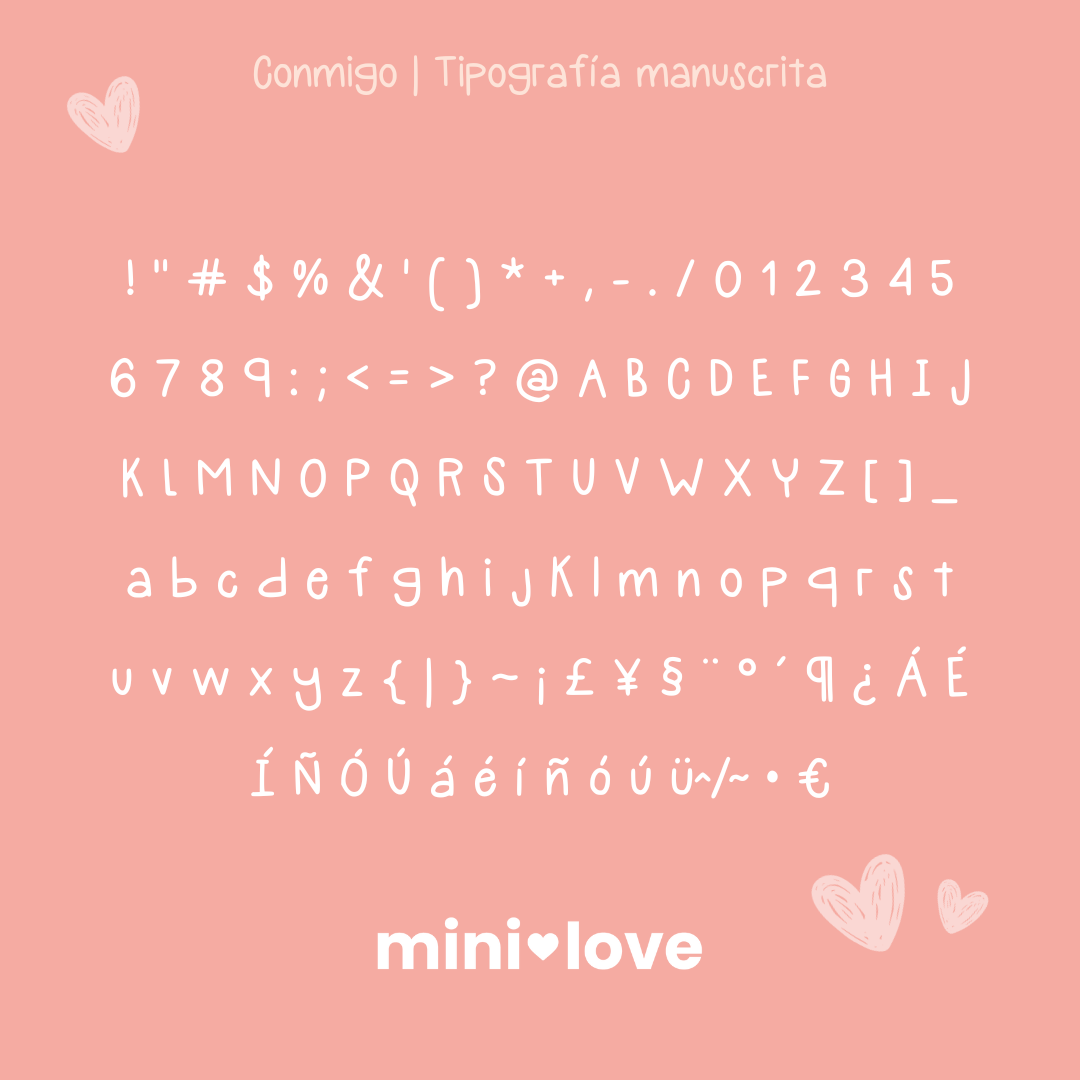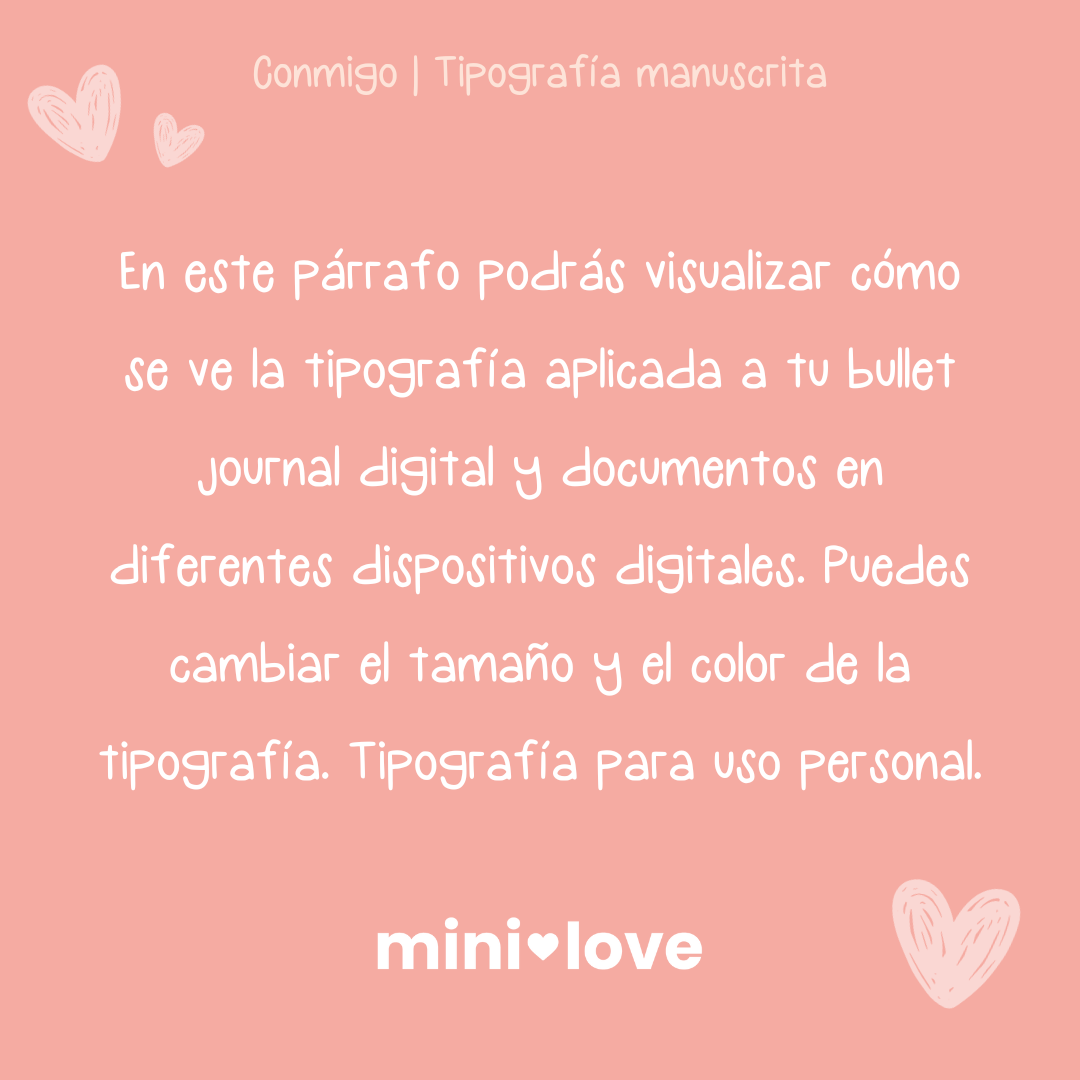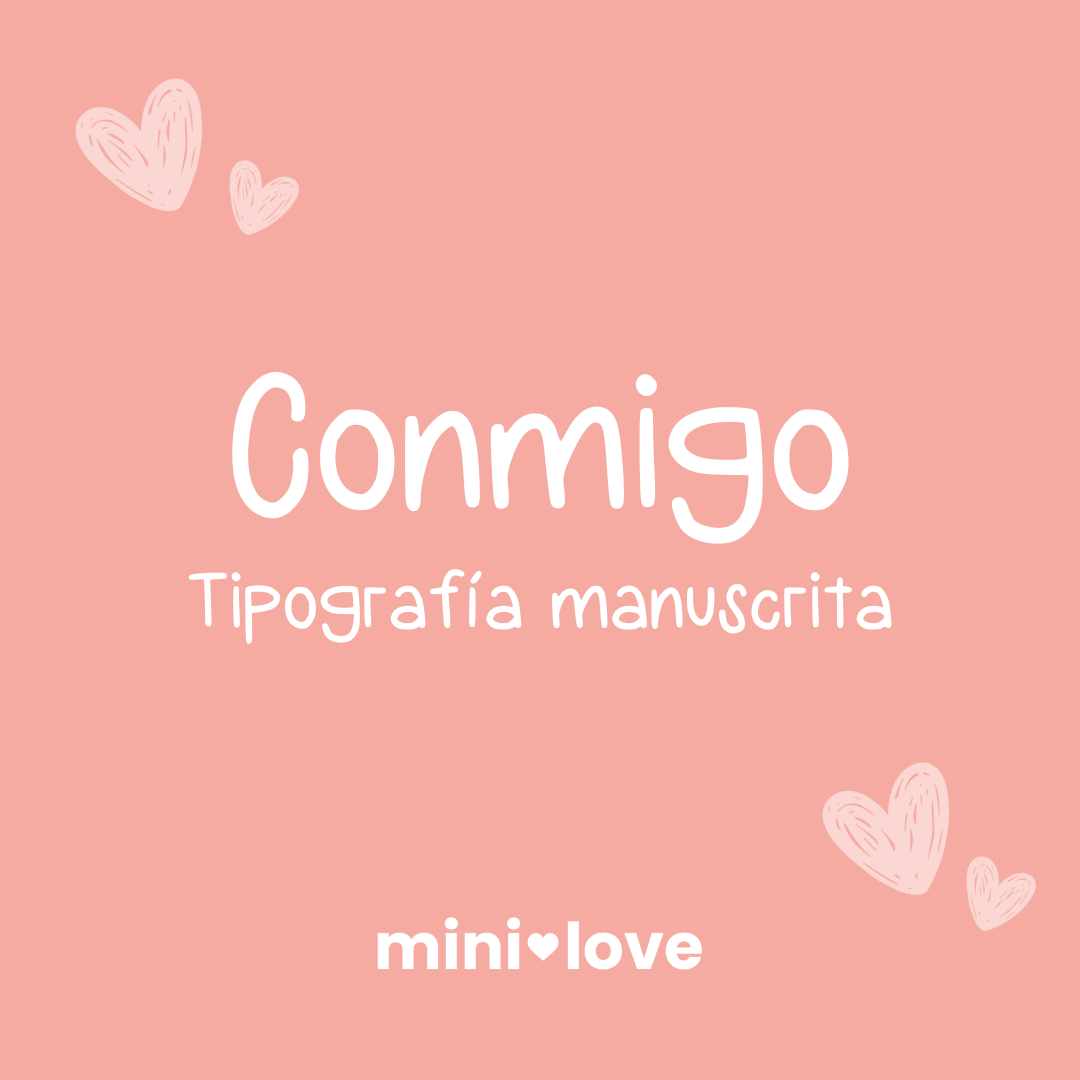
Tipografía Conmigo
Esta tipografía estilo manuscrito es la elección perfecta para darle un toque personal a tu bullet journal, apuntes, anotaciones y títulos. Transforma tus escritos en una experiencia única, como si estuvieras escribiendo con tu propia caligrafía.